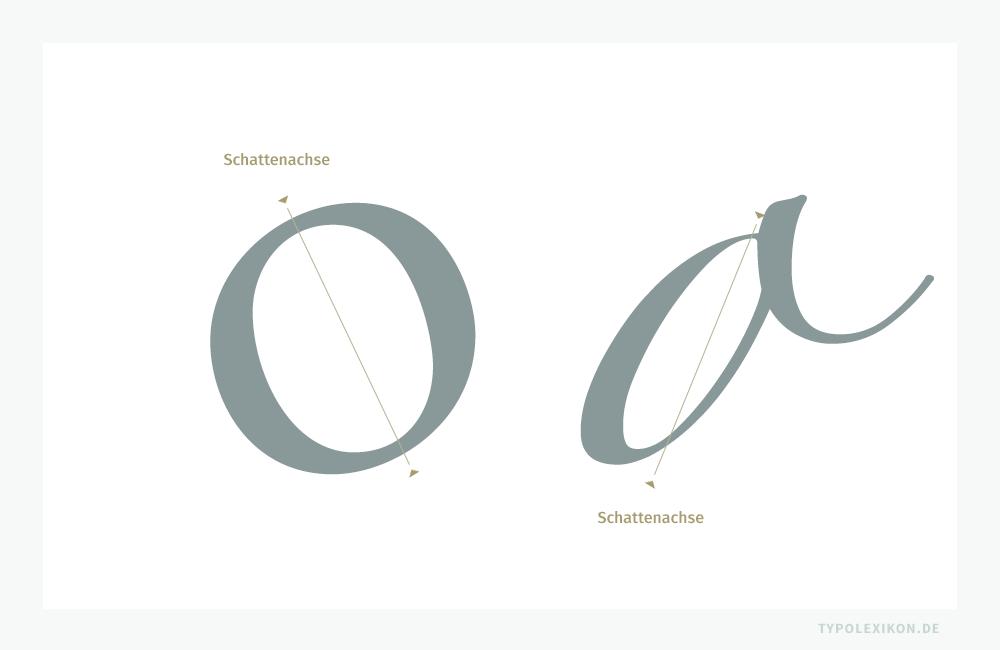
Schattenachse
Der Begriff »Schattenachse« stammt aus der Kalligrafie und wurde von der Typografie und der Schriftgestaltung übernommen. Bei handgeschriebenen bzw. kalligrafischen Lettern bezieht sich der Begriff auf eine imaginäre Achse zwischen zwei Koordinaten mit den geringsten Strichstärken eines Buchstabens oder Zeichens römischen Ursprungs. Festgelegt wird die Schattenachse durch den Duktus, der u.a. durch die Haltung und Führung eines Schreibgeräts, beispielsweise einer Breit- oder Rohrfeder, geprägt wird.
Insbesondere bei runden Buchstaben römischen Ursprungs, beispielsweise beim »o«, verläuft die imaginäre Schattenachse zwischen den zwei Koordinaten mit den geringsten Strichstärken, welche allerdings das Schriftzeichen nicht symmetrisch teilen muss. Links die Guardi von Reinhard Haus (*1950) und rechts die Zapfino von Hermann Zapf (1918–2015).
Insbesondere bei runden Buchstaben mit Binnenräumen (Punzen), z.B. beim »o«, verläuft die Schattenachse zwischen den Stellen mit den geringsten Strichstärken und halbiert auf den ersten Blick das runde Schriftzeichen. Die Schattenachse wird deshalb oft auch fälschlicher Weise als Symmetrieachse bezeichnet; fälschlicher Weise, denn die imaginäre Schattenachse teilt in den wenigsten Fällen ein Schriftzeichen in zwei gleich große Teile. Dieses Phänomen trägt zur Einzigartigkeit des Schreibduktus bei und ermöglichen es auch, individuelle Schreibstile zu identifizieren.
Die Schattenachse kann allerdings die Achsstellung eines Schriftzeichens beeinflussen, muss sie aber nicht. Bei gedruckten Schriften ist die Schattenachse nicht nur ein ästhetisches Element in der Schriftgestaltung, sondern auch ein wichtiges Merkmal zur Identifikation von Schriften hinsichtlich der Schriftklassifikation. So lassen sich klassische Drucktypen unterschiedlicher Epochen oft auch anhand der Ausrichtung der Schattenachse unterscheiden. Insbesondere Antiqua-Schriften und Gebrochene Schriften neigen dazu, charakteristische Neigungen, Strichstärken und Wechselzüge zu bevorzugen, die eine klare Identifikation und Einordnung ermöglichen. Bei serifenlosen Schriften, also Grotesk-Schriften, ist dieses wiederum selten zu finden.
Moderne Analysewerkzeuge, beispielsweise Deep Learning Software wie WhatTheFont ® von Monotype ®, 1) ermöglichen eine präzise Erfassung und Quantifizierung von Schattenachsen. Diese Methoden ermöglichen eine tiefgehende Untersuchung von Schriften und unterstützen die Entwicklung von Klassifikationsalgorithmen für Druckschriften und Screen Fonts.
Seit wann und warum der Begriff verwendet wurde oder woher er stammt, ist nicht bekannt. Etymologisch rührt der Begriff »Schatten« jedenfalls vom althochdeutschen Wort »scato« ab, was u.a. »Dunkelheit«, »ständiger Begleiter« oder »etwas kaum Erkennbares« bedeutet. Im kalligrafischen Kontext könnte sich dieser Wortteil vielleicht auf den durch Licht verursachten Schatten beziehen, der durch die Strichstärkevariation von Buchstaben oder anderen kalligrafischen Elementen entsteht. Der Begriff »Achse« hat seine Wurzeln im lateinischen Wort »axis«, was eine »Achse« oder »Drehachse« bedeutet. In der Typografie könnte das Kompositum vermutlich einfach nur metaphorisch verwendet worden sein, um eine imaginäre, optisch gefühlte Achse durch das Schriftzeichen zu beschreiben.